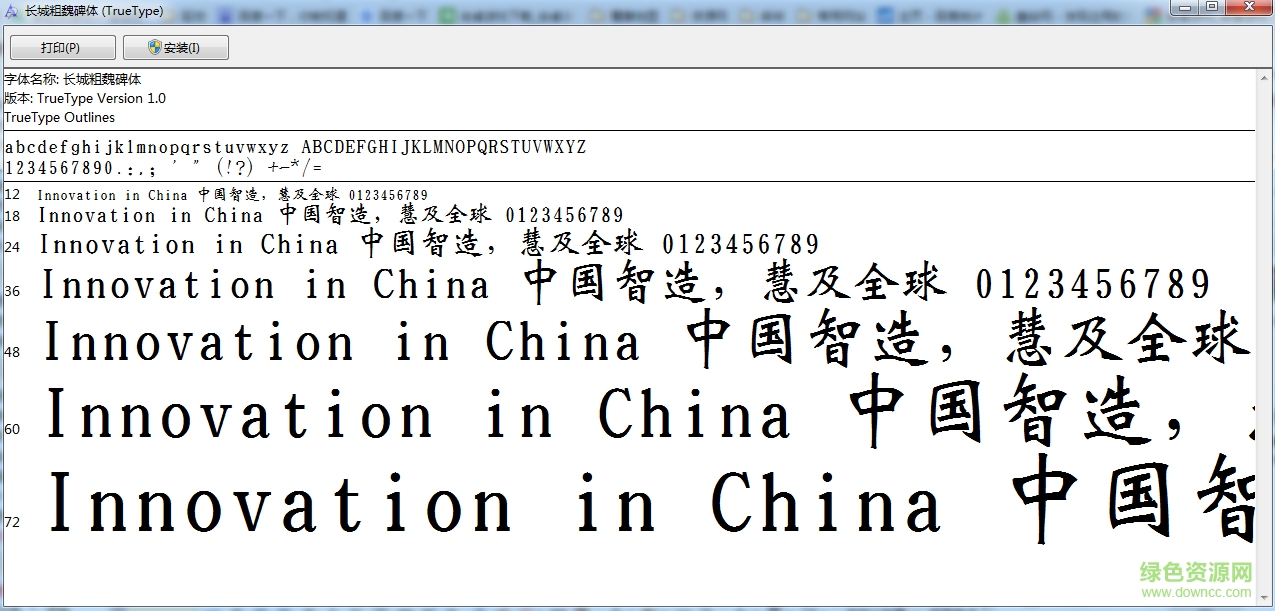
長城粗魏碑體是一款加粗了的魏碑簡體字體,筆畫嚴(yán)謹(jǐn)而飄逸、造型大方而簡約,是魏碑體的精華之作,使用于文字編輯、藝術(shù)設(shè)計、廣告創(chuàng)作等行業(yè),快來綠色資源網(wǎng)免費下載體驗吧!
魏碑書法筆劃嚴(yán)謹(jǐn)、樸厚靈動,豐腴不失于板刻,上承漢隸,下開唐楷,兼有隸楷兩體之神韻。它的書法藝術(shù)是在漢隸和晉楷的基礎(chǔ)上發(fā)展演化而來的,堪稱漢碑中的上品。古今書家對此碑都給予最高評價,可謂漢碑集成之碑。